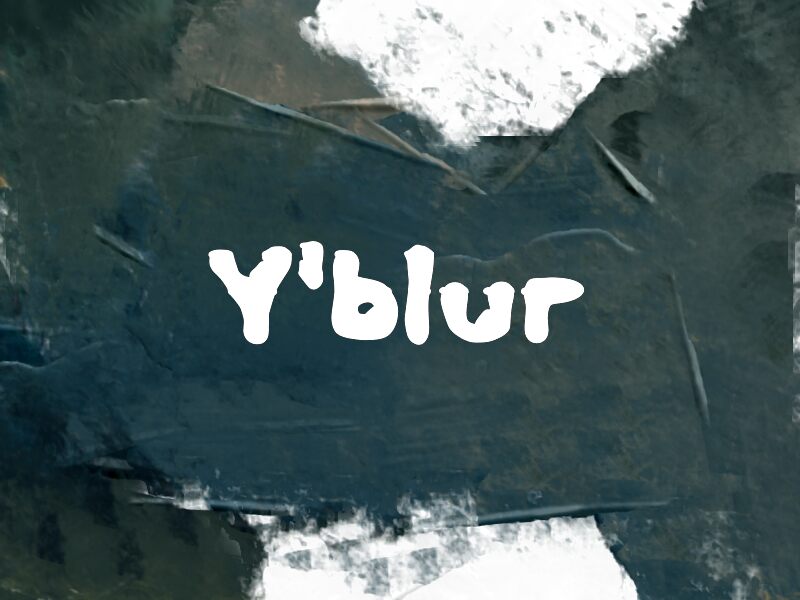
Y'blur
Y'blur é uma fonte display gratuita da Wep que utiliza silhuetas inchadas e irregulares, conferindo às letras uma aparência macia, flácida e levemente derretida. Os recortes ásperos e as pontas arredondadas criam uma textura marcante que percorre toda a fonte, fazendo com que a distorção pareça um elemento de design intencional e não apenas um efeito passageiro.
Esse ritmo irregular confere muita personalidade a títulos curtos em pôsteres, capas de álbuns, zines, designs de streetwear e flyers de eventos. É uma ótima escolha para adesivos ou cabeçalhos de redes sociais, onde as formas infladas e as bordas desgastadas fazem o trabalho visual sozinhas, dispensando ornamentos adicionais.